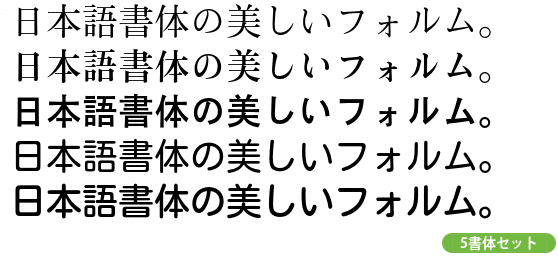
明朝体
株式会社モトヤ
モトヤ明朝3 Std
本文用は懐をバランス良く広く、見出し用は縦画の下にふくらみを持たせ楷書風の柔らかさを表現した、伝統的な明朝体です。
9,354字を収録したStd版。
令和合字に対応
モトヤ書体の開発は、1950年代から始まり現在に至っています。活字の製造販売を中心として創業し、活字が「印刷のもと」であることから「もとや」=「モトヤ」という社名になりました。
モトヤ書体は現在まで、鉛活字、タイプ活字、写植用文字版、デジタルフォント (ビットマップフォント・アウトラインフォント) と様々な組版手段に対応し、その製品形態を変えてきました。永年にわたる書体開発の歴史の中で、「可読性の良さ」と「文字の美しさ」を変わらず追求する老舗フォントメーカーです。